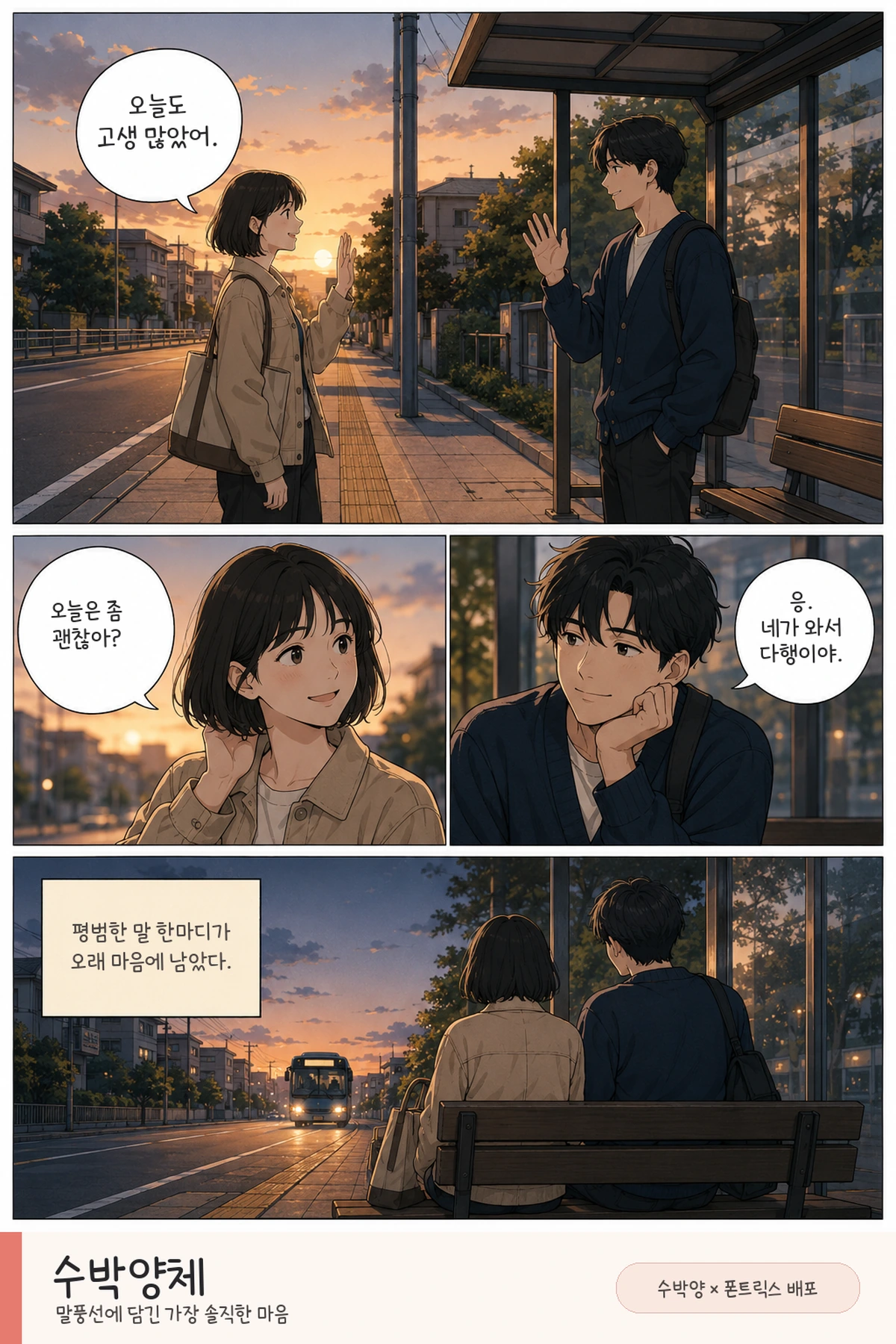
수박양체 — 수박양 X 폰트릭스에서 배포하는 무료 폰트입니다. 웹툰 말풍선에 쓰이던 작가의 글씨를 옮겨, 동글한 ㅇ과 독특한 쌍시옷이 그대로 살아 있는 손글씨체
네이버 웹툰 아홉수 우리들을 그린 수박양 작가의 손글씨를 폰트릭스가 서체로 옮긴 글꼴입니다. 웹툰 말풍선에 쓰이던 작가의 글씨가 원본입니다.
제작사가 무엇을 살렸는지 구체적으로 밝혀 두었습니다. 손글씨의 동글동글한 ㅇ꼴과 쌍시옷의 독특한 모양을 특징으로 그대로 살려 구현했다는 것입니다. 파일에서 재어 보면 받침이 붙을 때 글자 높이가 달라지는 탈네모틀이라 글줄에 손글씨다운 리듬이 남아 있습니다.
제 글씨체를 디자인으로 한 수박양체 폰트가 나왔습니다! <폰트릭스>에서 개발에 힘써주셨어요! 수박양과 폰트릭스 콜라보로 제작된 수박양체는 전부 무료로 이용하실 수 있습니다. 상업적 이용 역시 자유롭게 써주셔도 됩니다.